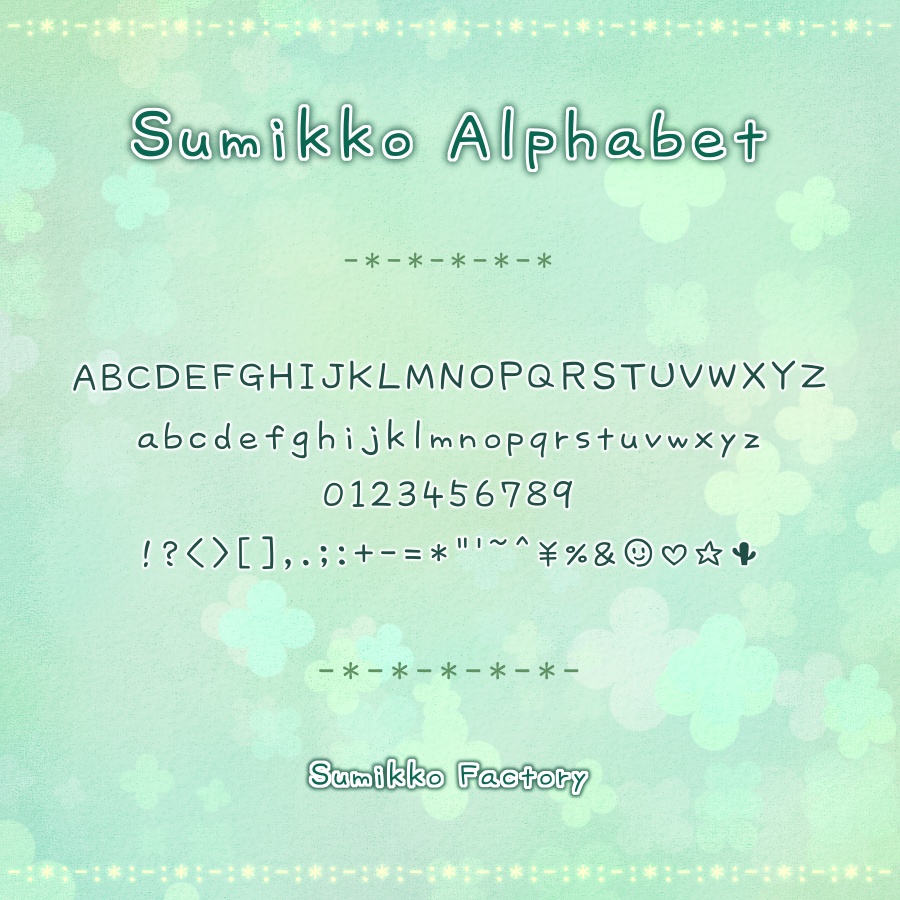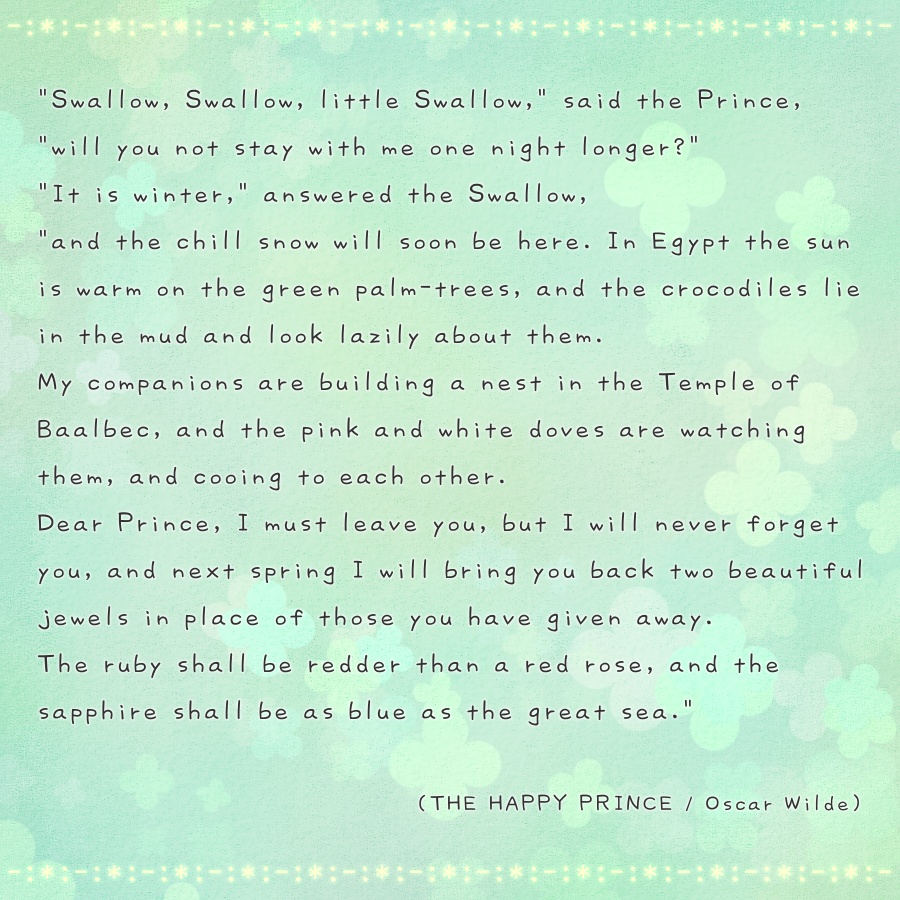
手書きフォント【Sumikko Alphabet】無料版
Sumikkoの手書き文字を元に作成した、アルファベットフォントです。英数字、一部の記号、絵文字が含まれています。 無料版・投げ銭版ともに、内容に違いはありません。 ★使用規約 ダウンロード前に以下の事項についてご確認ください。 このフォントを使ってできること ・個人使用(SNSでの使用、個人サイトでの使用、年賀状での使用等) ・商用使用(同人誌への使用、アフィリエイトに関わる使用、ショップサイトでの使用等) 禁止事項 ・公序良俗に反する行為、反社会的な行為に関連した使用。 ・フォトファイル自体の再配布、販売。 ・本フォントファイルを元にして、類似したフォントを作成する行為。 その他 ・本規約は事前の告知なく変更する場合があり、ご使用にあたっては、常に最新の規約に従うものとします。 ・本ファイルの使用に起因して不具合、損害等が発生した場合も、その責任を負いません。 ・本ファイルは武蔵システム(https://opentype.jp/)の(TTEdit)を使って作成しました。 絵文字の出し方 スマイル→ | ( Shift + \ ) ハート→ { ( Shift + [ ) 星→ } ( Shift + ] ) サボテン→ $ ( Shift + 4 )